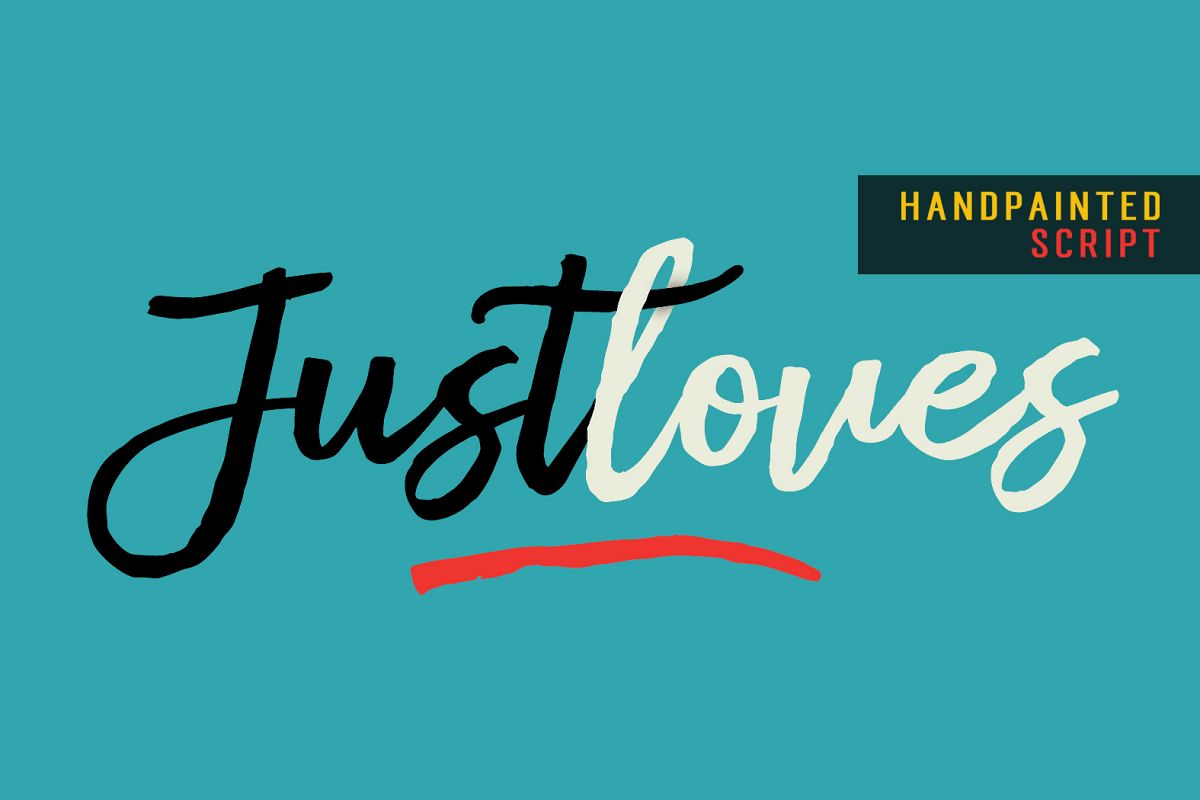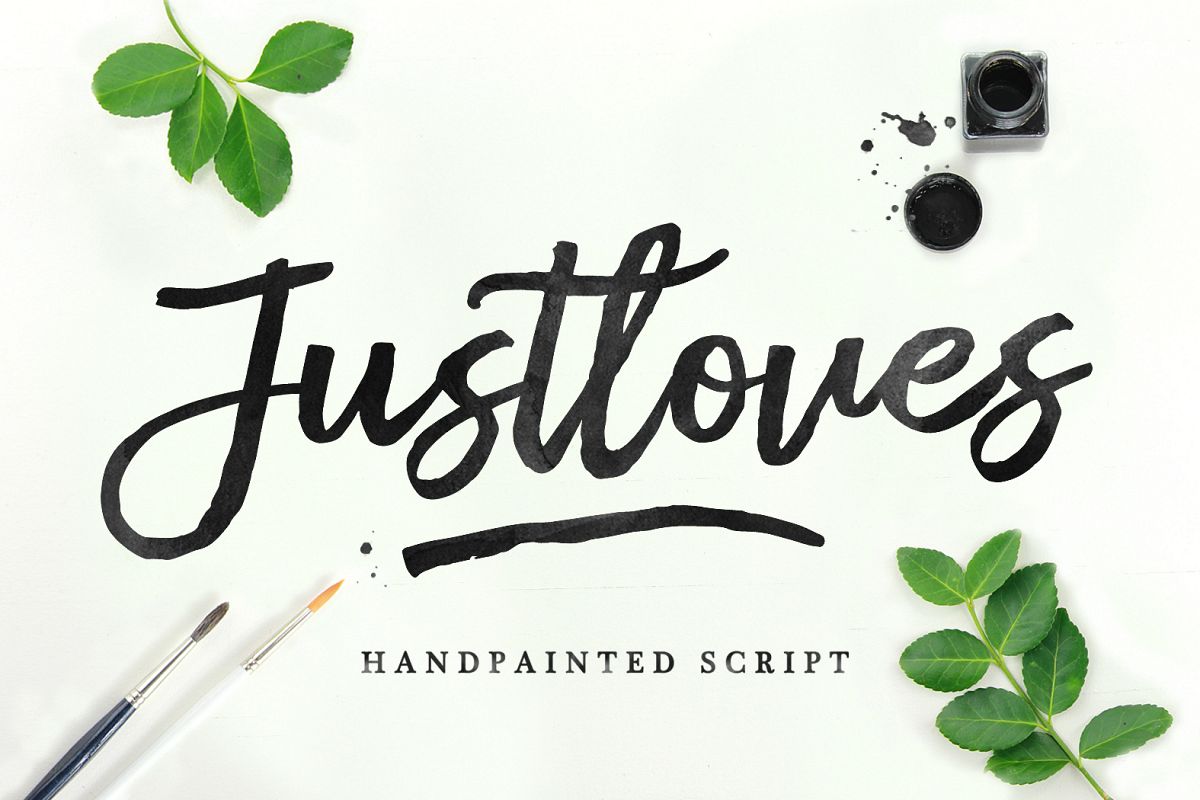
Justloves
Justloves  adalah font yang khusus dibuat dengan kuas yang terlihat alami,
font ini sangat unik dan menarik untuk desain Anda seperti sablon,
kartu bisnis, merek, logo, kartu ucapan, blog dan semua untuk desain pribadi Anda,
font termasuk beberapa pengikat dan alternatif yang menarik .